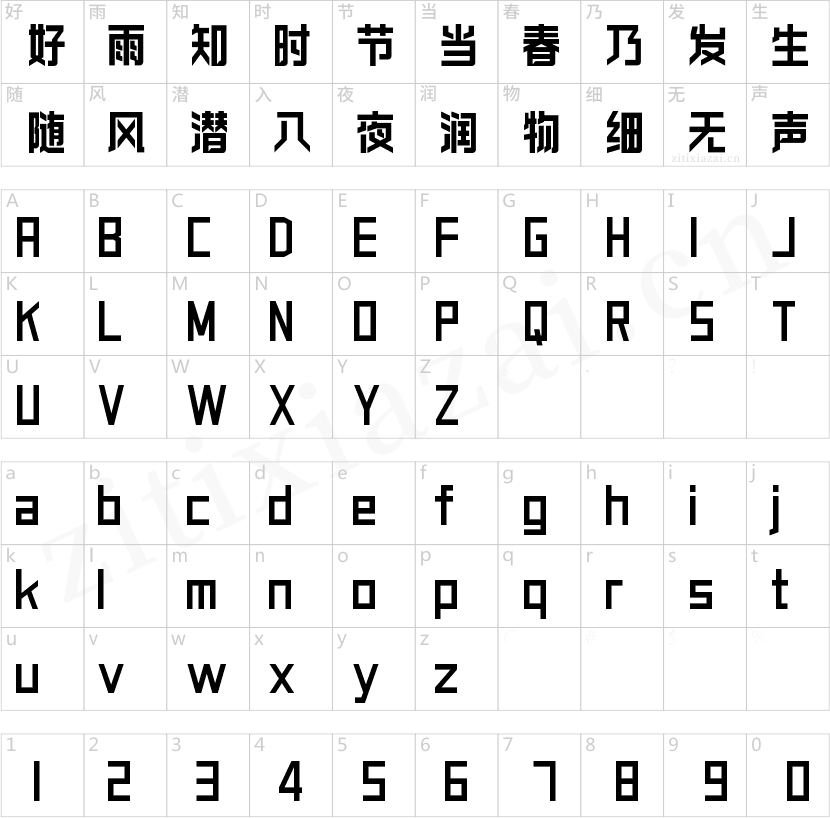
壹心机械体
壹心机械体,这款字体结构工整、笔画清晰,兼顾美观与易读性,适用于标题、正文、海报、包装、LOGO 等多种场景。字形优雅稳定,风格百搭耐看,适配日常排版与创意设计,让文字呈现更舒适、更具质感。壹心机械体一笔一画,皆是细节,以均衡的比例、流畅的线条打造舒适视觉体验,字形端正大气,风格简约现代。无论是商业设计、品牌宣传还是日常排版,都能轻松驾驭,让文字更有格调与力量。壹心机械体字体下载。